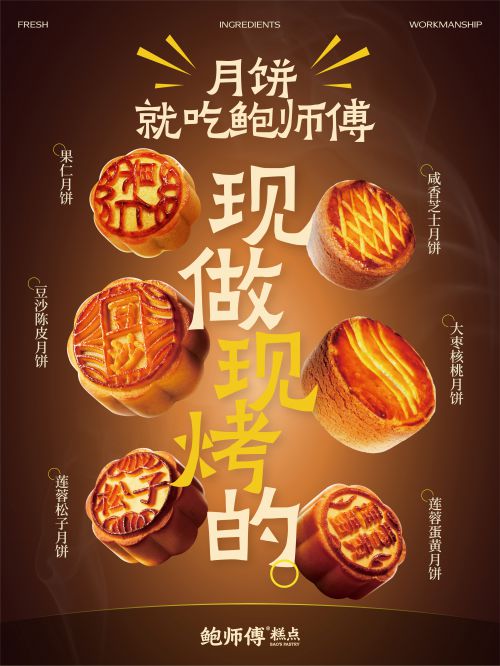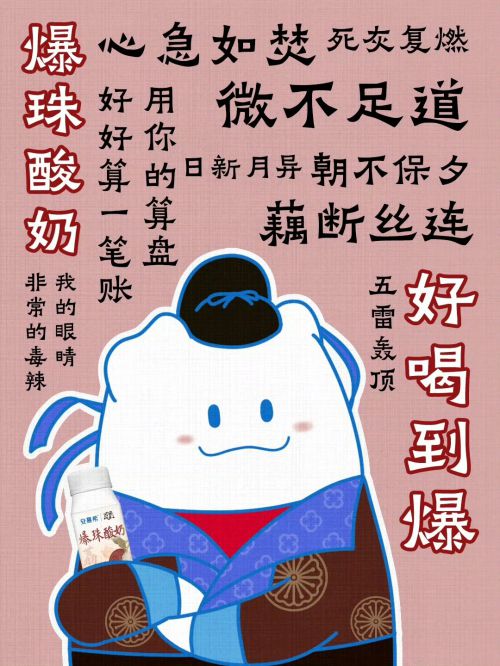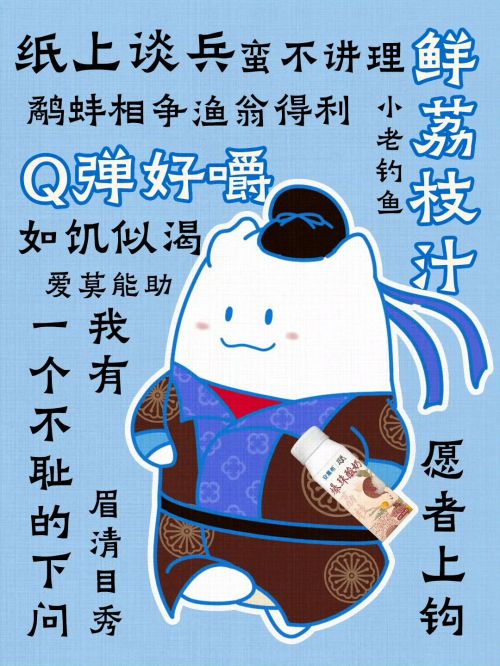
阿里妈妈刀隶体
### 阿里妈妈刀隶体字体简介 阿里妈妈刀隶体是一款融合中国风与创意设计的古典风格字体,【免费商用】授权使其成为设计领域的实用之选。字体灵感源自爨宝子碑的经典笔法,通过修长字形与适中中宫结构,营造出兼具力量感与艺术性的视觉效果。 其显著特征在于三角点折弯与横画“雁尾”的方劲处理,配合方头与圆头笔画的交替使用,形成极具冲击力的粗细对比。斜切装饰元素的加入更凸显锋芒外露的艺术个性,展现出“朴茂倔犟”的独特气质。 阿里妈妈刀隶体打破传统隶书的均匀结构,以大胆的结字布局实现“险中求正”的美学平衡,介于隶楷之间的字形特征既保留古典书法的厚重底蕴,又通过断开笔画的设计增强现代设计适配性。适用于国潮品牌标识、文化海报、包装设计等多元场景,为设计项目注入兼具历史韵味与商业价值的视觉符号。